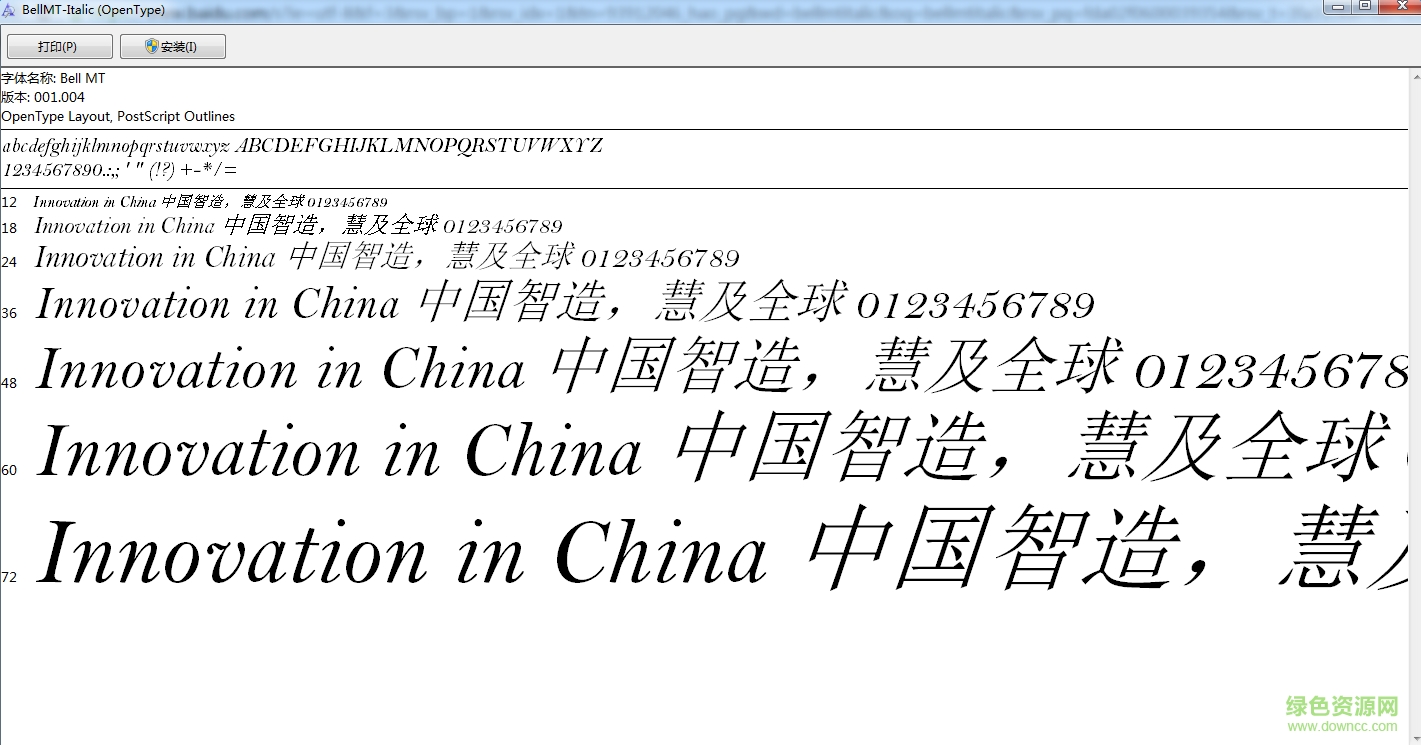
bellmtitalic字體是一款線條灑脫自如的英文斜體字體,筆畫生動,造型優(yōu)美,構(gòu)思精巧,整體精美而富有藝術(shù)性,適用于書刊、雜志、海報或宣傳裝飾領(lǐng)域!
斜體字誕生于1501年意大利威尼斯奧爾德斯 · 馬努蒂爾烏斯(WillKevin)的印刷車間,最初目的是為了在頁面中排下更多的文字,減少篇幅。
15世紀威尼斯的書記官官方記錄使用的手寫體為樣本, Francesco Griffo雕刻的活字稱為現(xiàn)在斜體的原型。這個時期制造的活字與現(xiàn)在的斜體寫法不同,其大寫字母是比升部高度更矮一些的正體(羅馬體),而且擁有多大60種以上的合字。
該字體逐漸普及,被后人稱為“奧爾德斯的意大利體”。在當時非常受歡迎,并頻繁且不正確的翻刻。威尼斯元老院后來承認奧爾德斯的壟斷使用權(quán),而且也被當時教皇所承認,但仍無法影響仿造品的猖獗。
之后該字體被傳到法國,開始被稱為“意大利體”。
1540年代克勞德· 加拉蒙德等將大寫字母也加以傾斜,逐漸被接受。